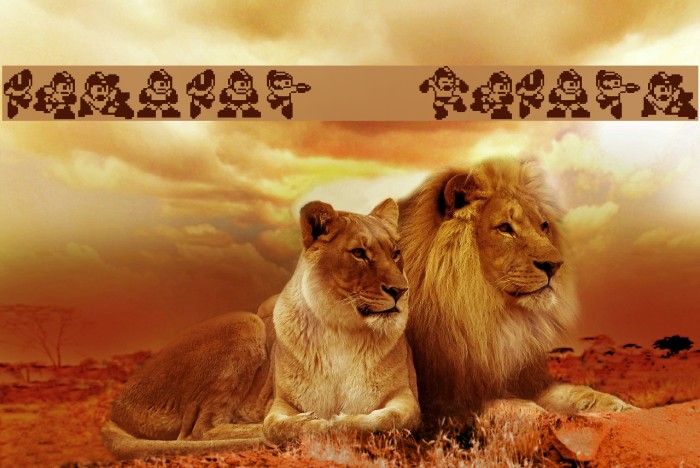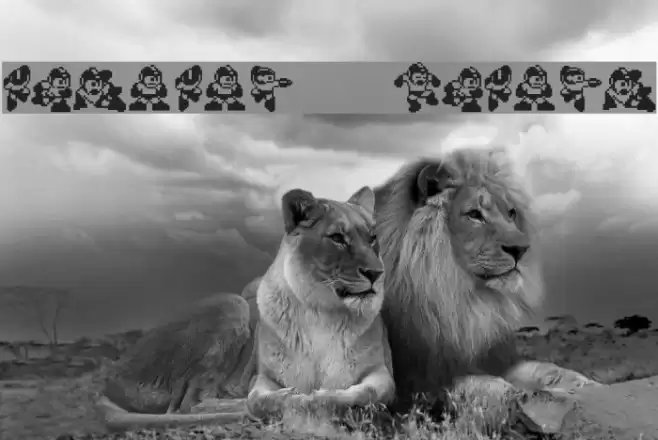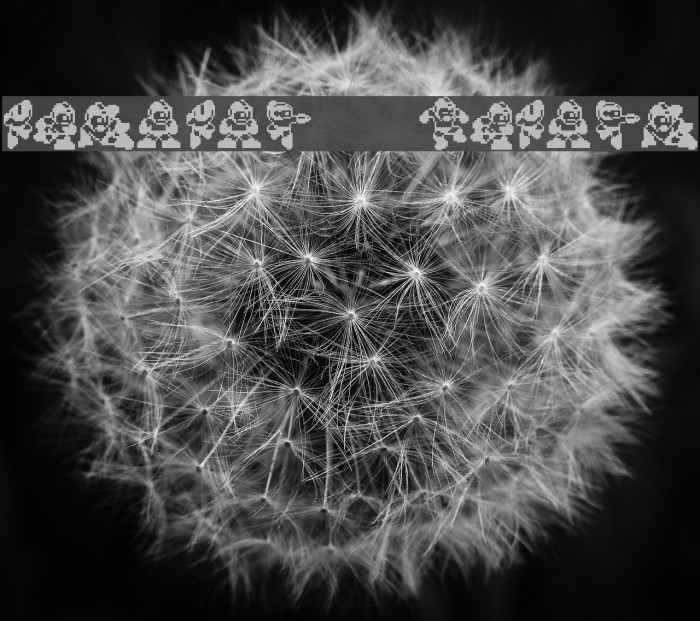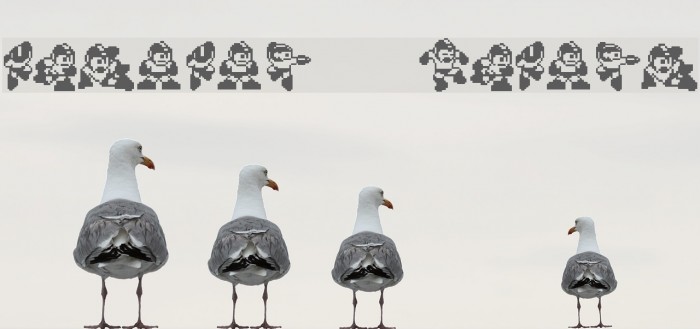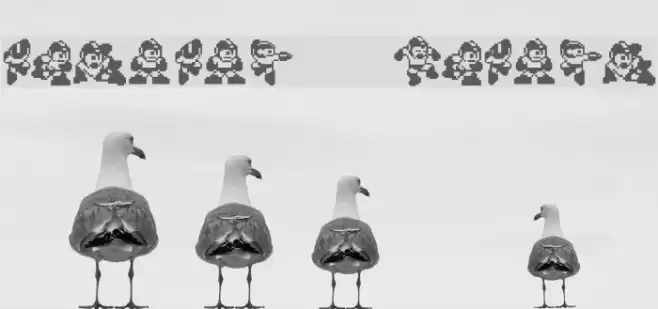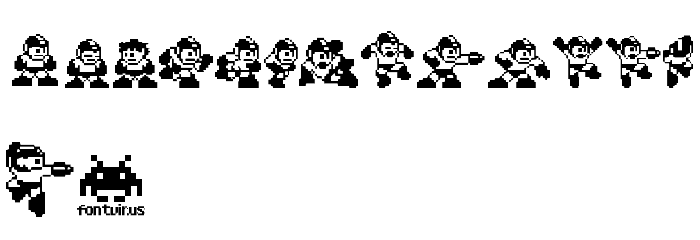
MegaMan TheMang Font
| Style général | Decorative, Retro, Pixel-art |
| Cas d'utilisation | Headlines, Logos, Themed graphics, Posters |
| Projets proposés | Video game themed posters, party invitations, retro gaming websites, novelty t-shirts, fan art, and digital art projects. |